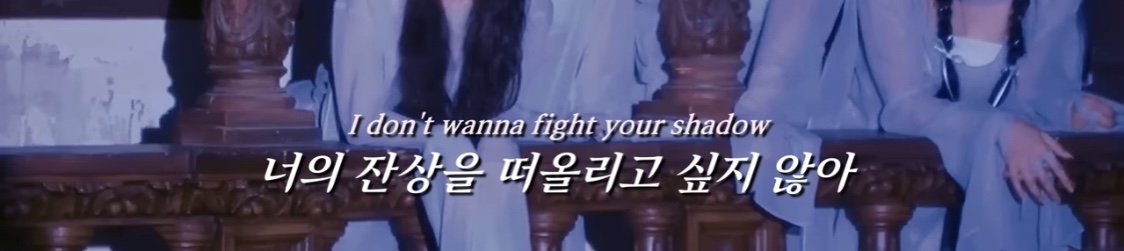
정말... 알고싶은 글씨체
아래 사진에 사용된 글씨체를 꼭 찾아내고 싶어요
다른 비슷한 글씨체로는 도무지 만족이 되질 않아서요
아시는 분이 계시다면 부디.. 부탁드립니다 T-T
아리따 부리 Bold 정도에 기울기를 적용한 것 같네요 https://www.sandollcloud.com/font/719.html